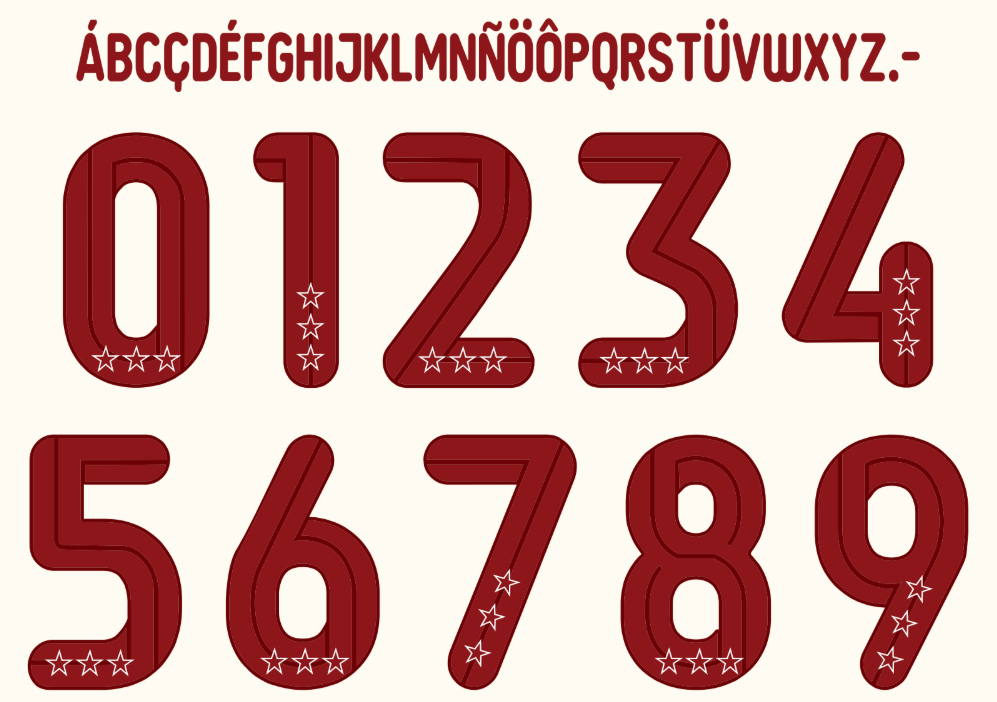
A temporada 2026 marca uma nova era para o Club Universitario de Deportes. Após o sucesso recente e a consolidação de sua hegemonia no futebol peruano, a Marathon lançou os novos uniformes que vestem o gigante “Merengue” na busca por mais um título nacional e na campanha continental.
Para designers, editores de PES/eFootball e colecionadores de mockups, a fidelidade visual é tudo. A nova tipografia utilizada nas camisas Crema (titular) e Guinda (reserva) reflete a modernidade que o clube busca, sem perder a essência clássica de sua rica história. A fonte deste ano abandona os traços arredondados de temporadas anteriores para adotar uma estética mais agressiva e tecnológica.
Estilo visual da tipografia
A fonte desenvolvida pela Marathon para a temporada 2026 do Universitario se destaca pela legibilidade e impacto visual.
- Geometria e Traços: Trata-se de uma tipografia sans-serif (sem serifa) com estrutura condensada e ângulos retos. Diferente de anos anteriores, os números possuem cortes diagonais sutis nas extremidades, conferindo uma sensação de velocidade e movimento, alinhada ao conceito de alta performance da marca esportiva.
- Aplicação no Uniforme:
- Home (Titular): Na tradicional camisa creme, a fonte é aplicada em cor Guinda (Vinho), criando o contraste clássico que identifica o clube.
- Away (Reserva): No uniforme vinho, a numeração aparece em Creme ou Dourado, dependendo da versão (Liga ou Copa), garantindo destaque imediato.
- Personalidade: A fonte transmite robustez e tradição renovada. Ela é limpa o suficiente para ser lida à distância nos estádios e detalhada o bastante para brilhar em transmissões HD e 4K.